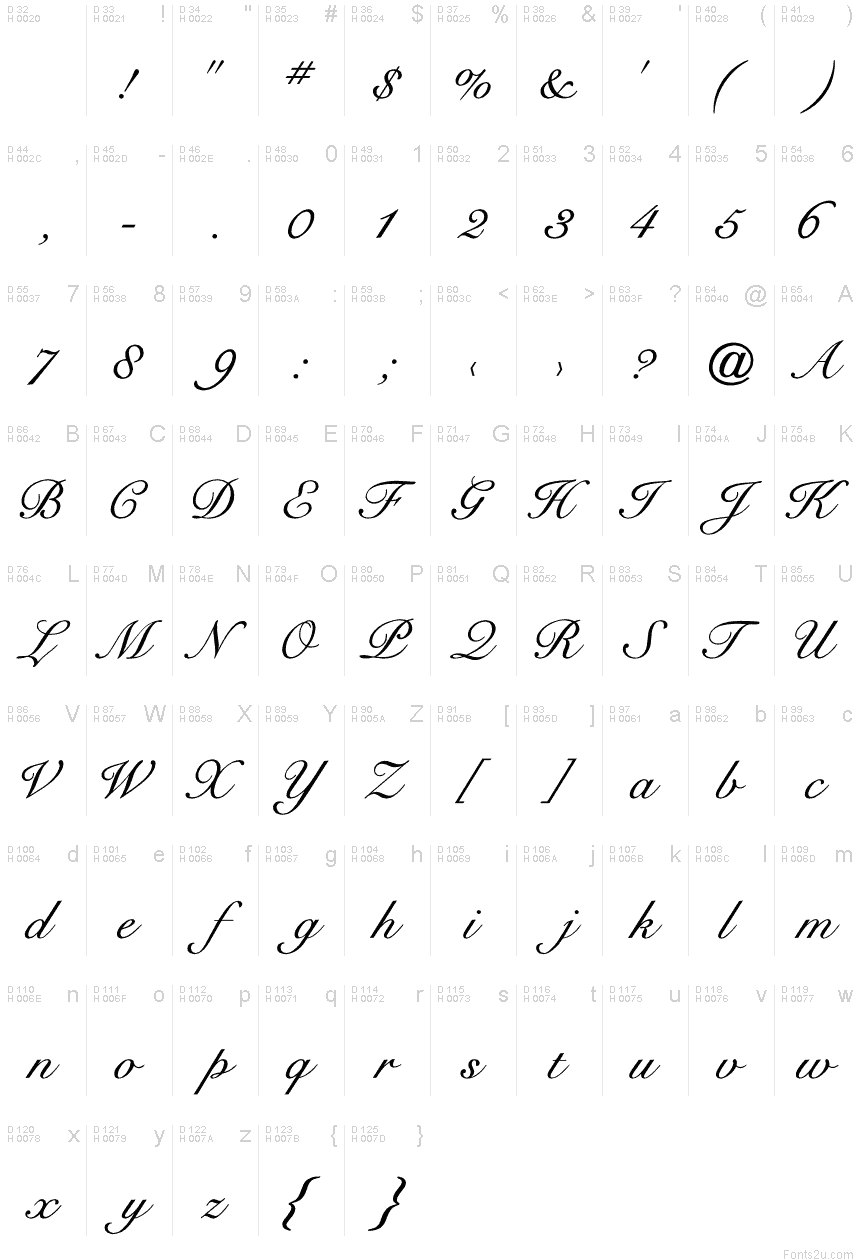
Шрифт Cygnet Round от Artful Bodger — это бесплатный каллиграфический гарнитур с плавными штрихами и изящным рукописным ритмом. Буквы мягко перетекают друг в друга, создавая ощущение «живых» чернил, что делает шрифт одновременно аккуратным и индивидуальным. Он придает тексту утонченный, слегка ностальгический характер, не выглядя при этом чопорно.
Используя Cygnet Round, вы добавите элегантности свадебным приглашениям, логотипам бутиков, упаковке, открыткам, сертификатам и романтическим цитатам. Этот бесплатный шрифт лучше всего раскрывается в крупном кегле, позволяя полюбоваться его петлями и изгибами, а для основного текста или мелких деталей он отлично сочетается с простыми гротесками.